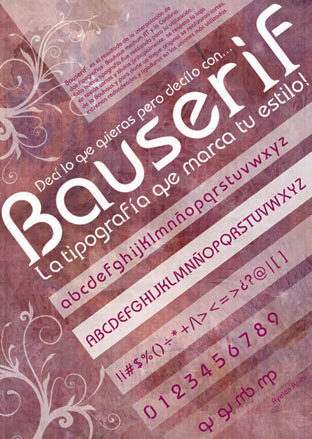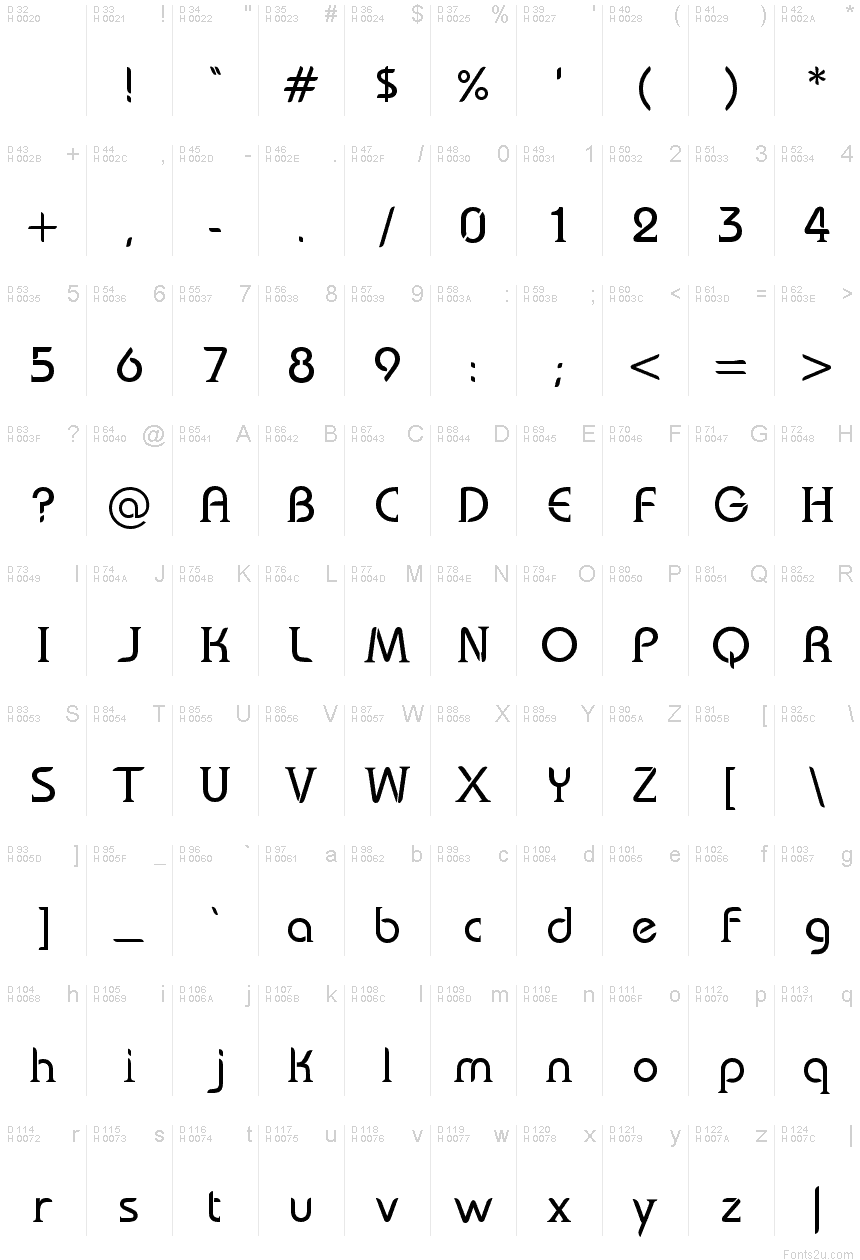
bauserif
Bauserif od Bitstream to darmowy krój pisma w stylu Bauhaus o płynnym, geometrycznym rytmie i wyrazistym klimacie cyfrowego revivalu lat 90. Litery bazują na niemal kołowych kształtach, miękkich rogach i zredukowanych łączeniach, dzięki czemu słowa wydają się spokojne, zwarte i lekko futurystyczne, a nie surowe czy mechaniczne.
Naturalnie pasuje do nagłówków plakatów, okładek płyt, projektów logo, szyldów sklepowych i tytułów, gdzie ten darmowy font wnosi retro-nowoczesny nastrój bez zbędnego zadęcia. Ponieważ kształty są tak zaokrąglone i zredukowane, Bauserif najlepiej sprawdza się w krótkich formach – kartach tytułowych, logotypach i krótkich akcentach redakcyjnych, gdzie jego czysta, zaokrąglona sylwetka może grać główną rolę.
BauseriF to efekt interpolacji dwóch krojów pisma: Bauhaus Medium BT oraz Cambria.
Zachowano oryginalny „letterbox” (ramkę) kroju Bauhaus.
W najczęściej używanych łączeniach dodano wcięcia, zaokrąglone końcówki i ligatury.